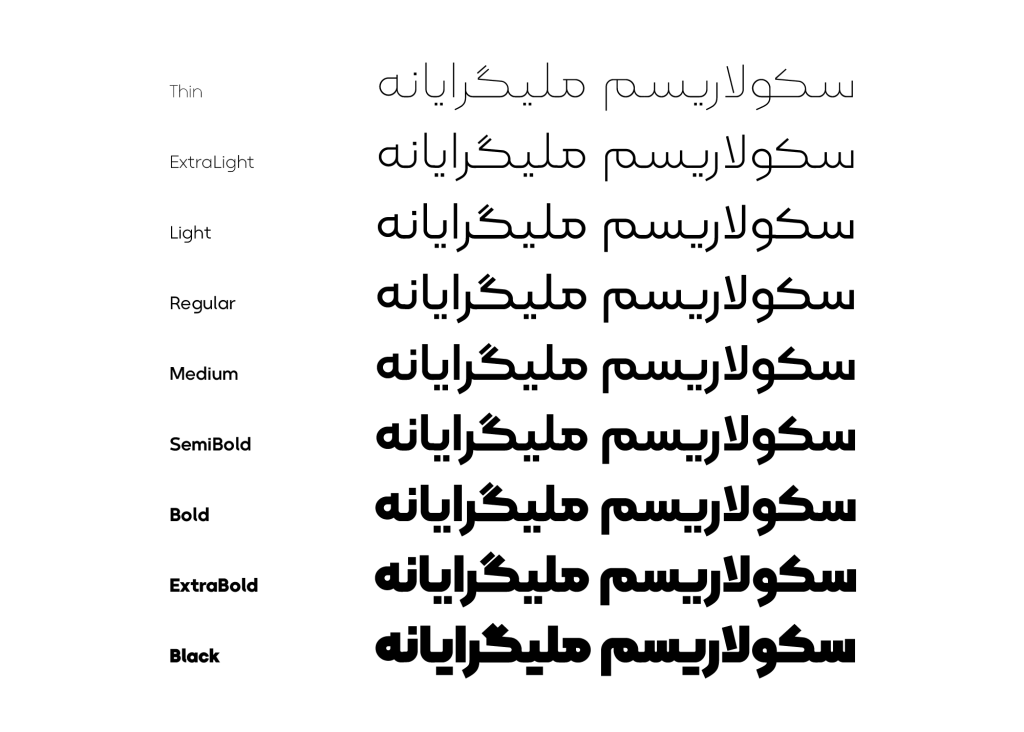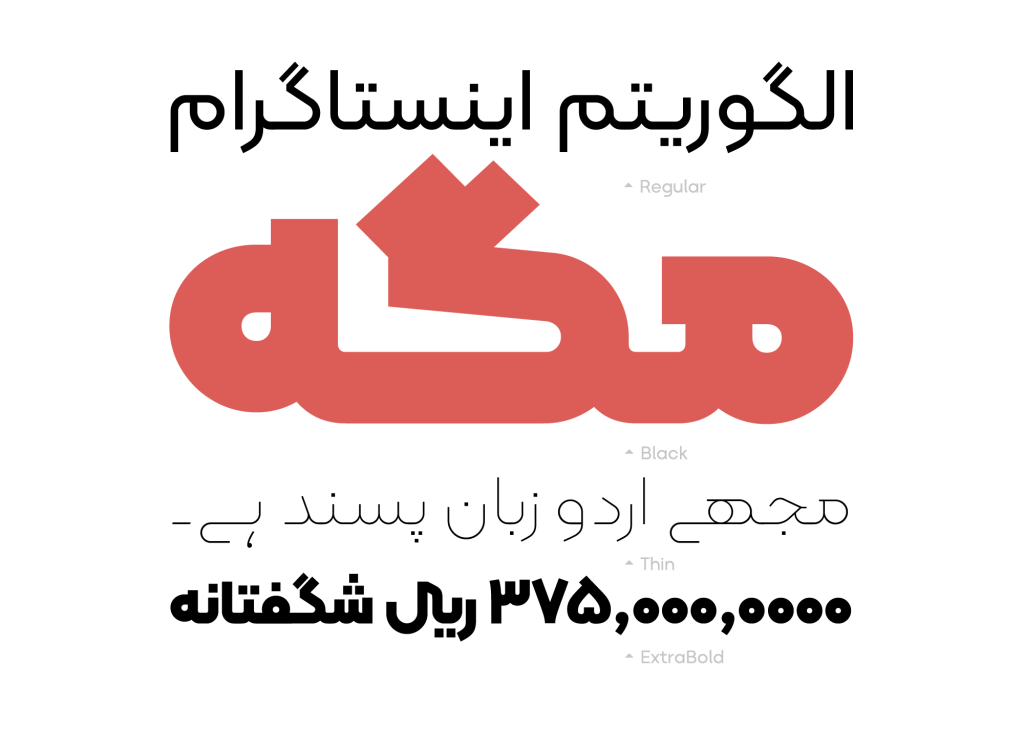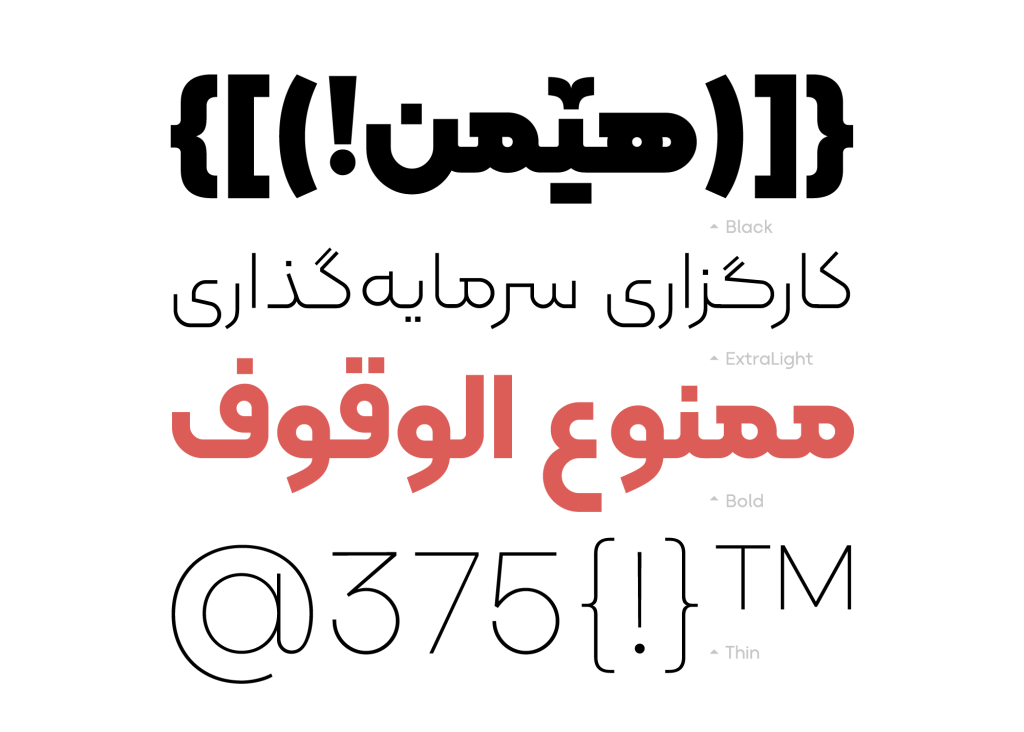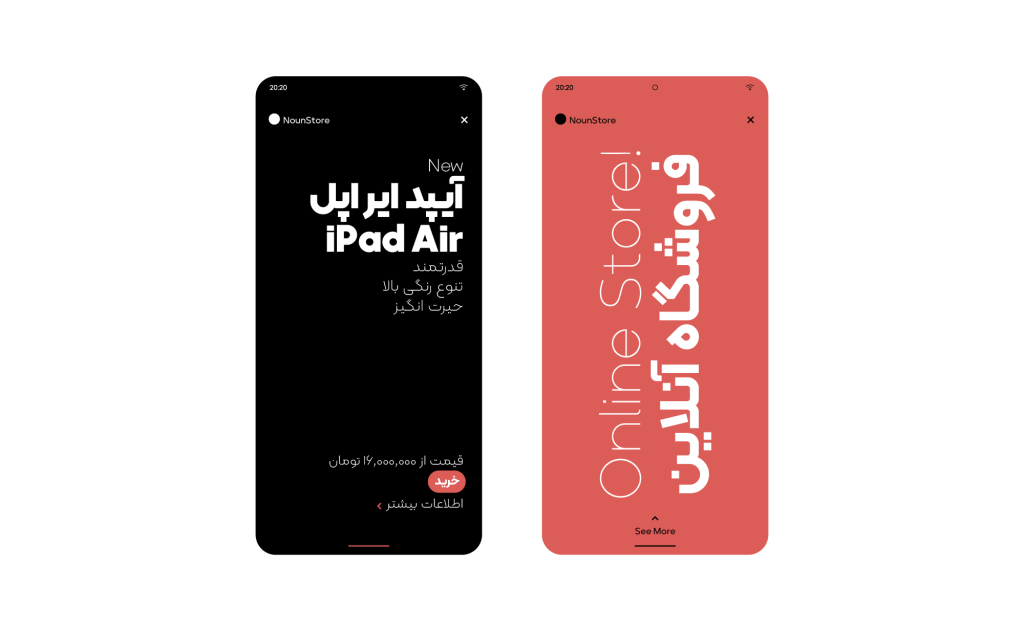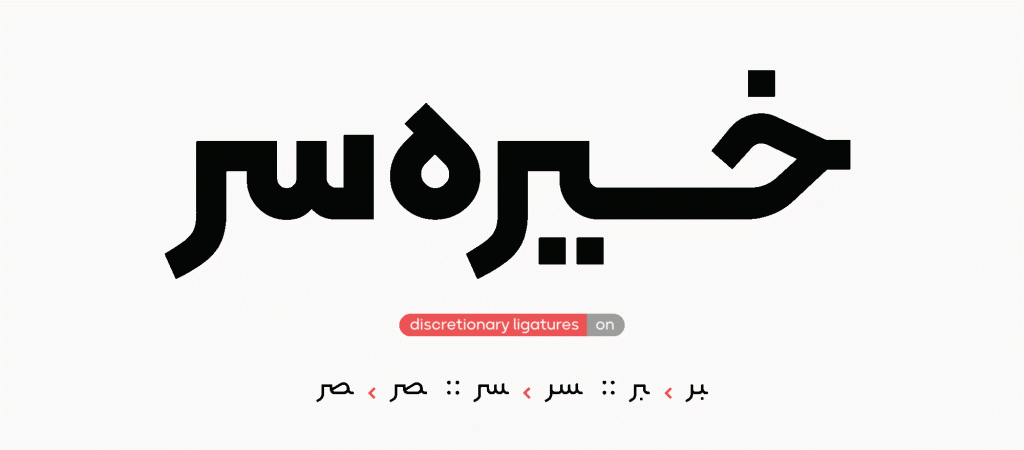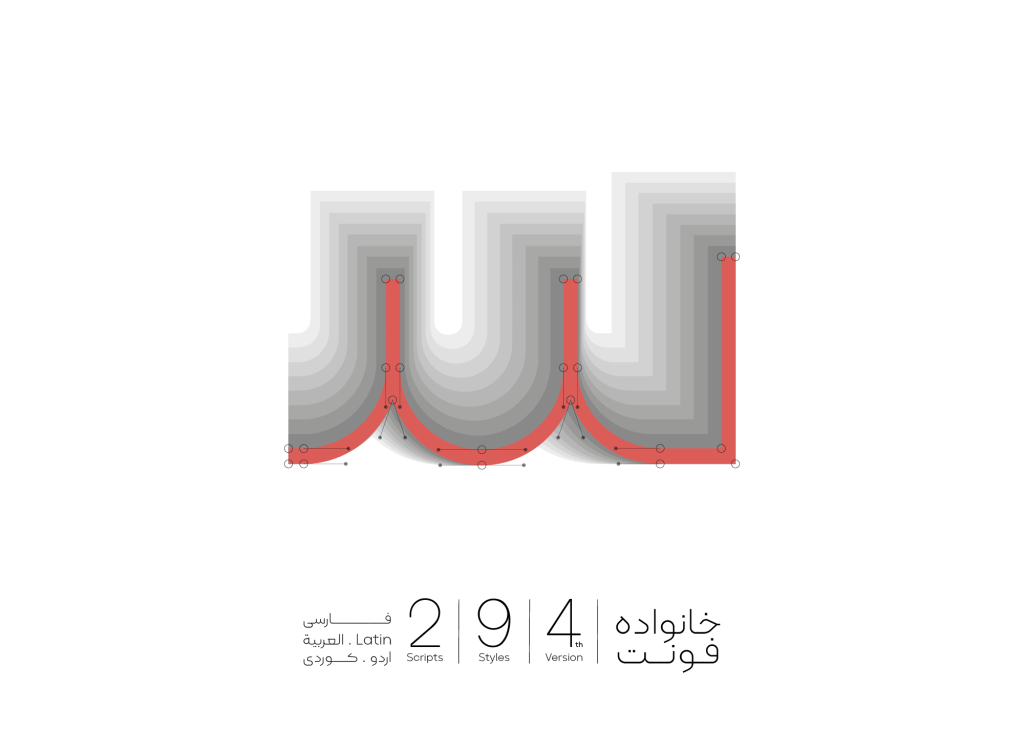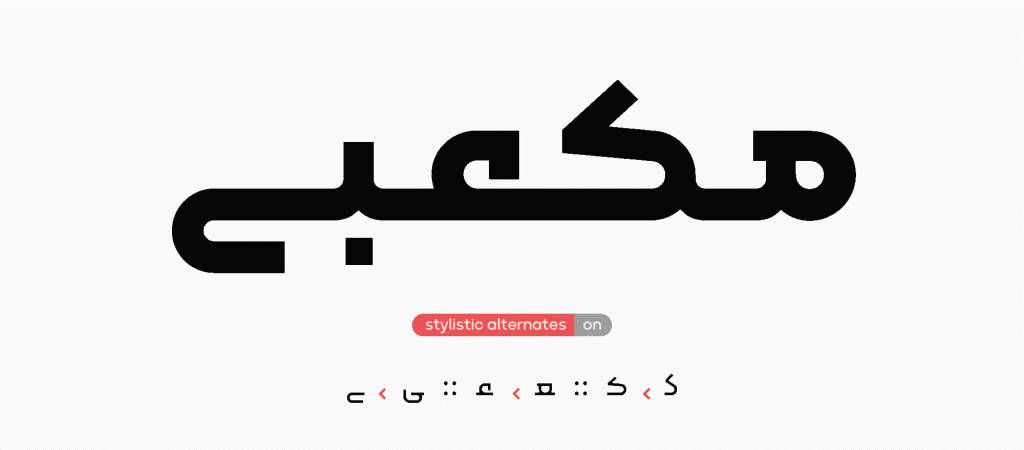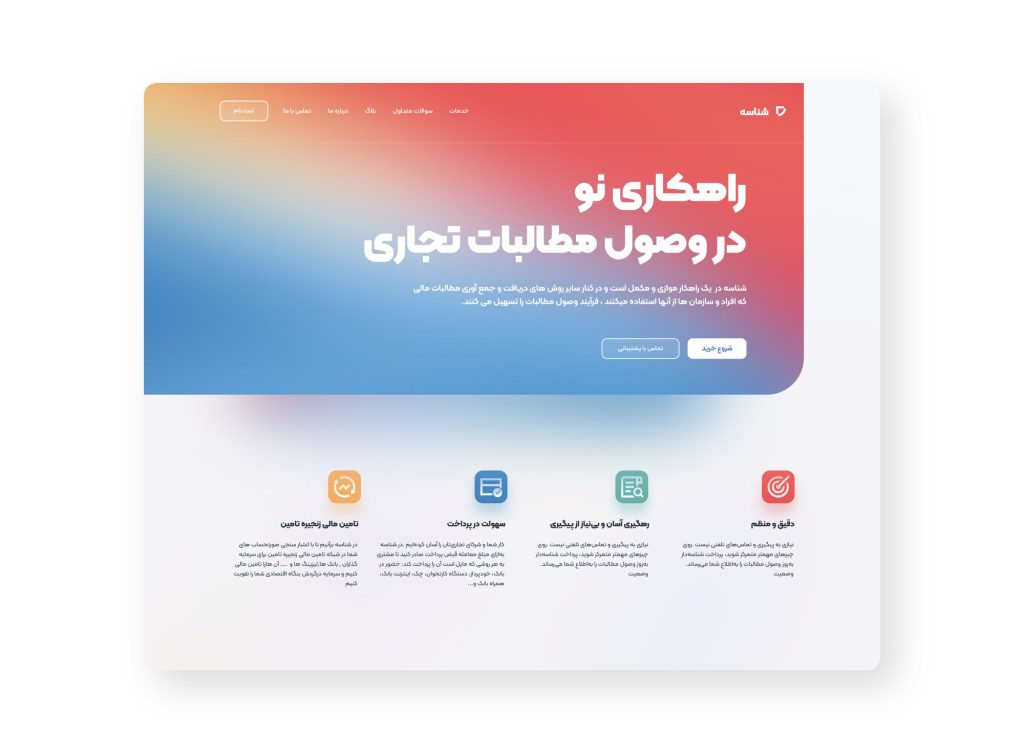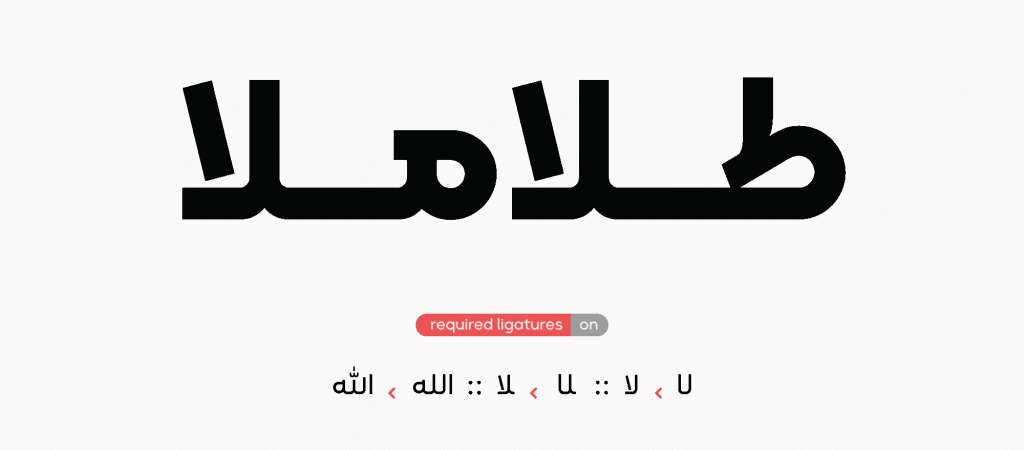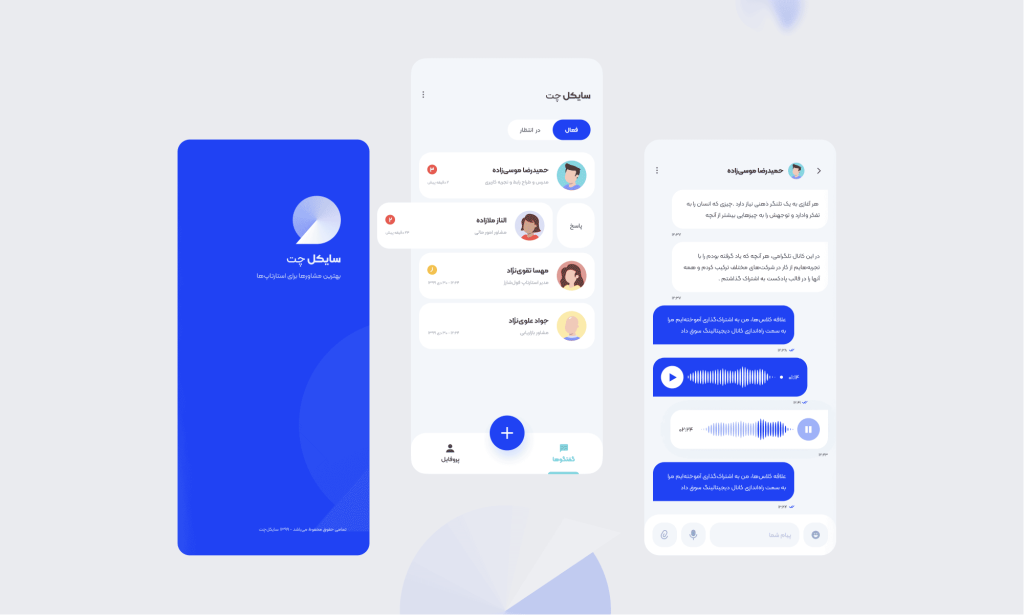
فونت کلمه
فونت کلمه، قلمی که توسط آقای رضا خادم طراح نام آشنای تایپ فیس های فارسی ابداع شده است. از سایر طراحی های آقای خادم که از نقطه نظر شباهت و هم خانوادگی نزدیک به کلمه می باشد می توان به فونت مدام اشاره نمود. این تایپ فیس هندسی از نوع منولاین بوده و فرم های نرم و منعطف در تار و پود این قلم مشاهده می شود.
کلمه مناسب برای تیتر های تبلیغاتی و مطبوعاتی و فضای شبکه های اجتماعی جهت جذب نگاه ها به خود می باشد. در متون و عناوینی که قصد برجسته نمودن و تکیه بر تواناییهای خاصی را در اهداف خود دارند و به خصوص شاخص نمودن نکات کلیدی می توان با اطمینان گفت کلمه انتخابی بسیار مناسب می باشد.
این تایپفیس برای زبان فارسی، عربی و انگلیسی طراحی و از زبانهای اردو و کردی نیز پشتیبانی میکند.
کلمه قلمی در حال به روز رسانی و رشد و نمو می باشد در نسخه چهارم این خانواده ، با اصلاحاتی نسبت به نسخههای پیشین و اضافه کردن حالتهای جایگزین حروف و پشتیبانی از زبانهای جدید ارایه گردیده است.
پشتیبانی کلمه از حروف جایگزین
در بسته این محصول تعدادی ترکیبات جایگزین اختیاری وجود دارد مزیت های بی شمار آن از جمله ایجاد تنوع و افزایش زیبایی که میتوانید به صورت دستی این ترکیبات اختیاری را در نرمافزارهای گرافیکی فعال کنید. این خانواده در پشتیبانی از وزن ها کامل است و با ۹ وزن مختلف از خیلی نازک تا سیاه تنوع کاملی از ضخامت و تیرگی را در اختیار شما قرار میدهد.